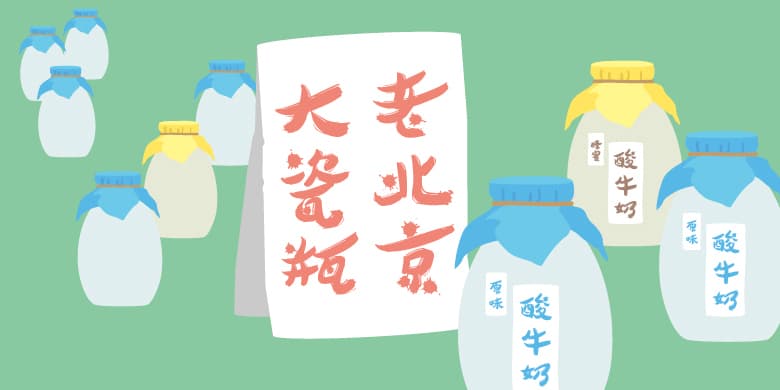
方正苏新诗毛糙体-
品牌:方正字库设计师:苏新诗发行时间:2020字库编码:大陆简体(GB2312-80)分类:创意书写字体属性:精品字
《方正苏新诗毛糙体》笔画粗糙,结构犀利,神态不羁飘逸,兼广告体、童趣、隶书书法为一身。字形给人一种没有经过精细的加工、未经修饰纯天然的感觉。适用于卡通设计、广告设计、平面设计、印刷包装、报纸杂志等行业。